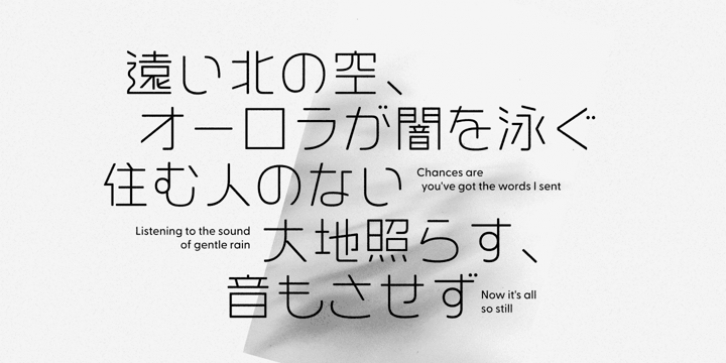
Future updates will add further kanji, including rare name and geographic glyphs.
グレイクリフã¯ã€ã™ã§ã«ãƒªãƒªãƒ¼ã‚¹ã—ã¦ã„ã‚‹ Greycliff CF サンセリフ書体ã«ã²ã‚‰ãŒãªã‚„æ¼¢å—ãªã©ã®æ—¥æœ¬èªžãŒæ–°ã—ãè¿½åŠ ã•れãŸãƒ•ォントã§ã™ã€‚大ããªç‰¹å¾´ã¨ã—ã¦ã€ã‚°ãƒ¬ã‚¤ã‚¯ãƒªãƒ•日本語フォントã¯ãƒãƒ¼ãƒžå—(ラテン文å—)ã®ãƒ•ォントデザインã¨çµ±ä¸€ã•れãŸãƒãƒ©ãƒ³ã‚¹ã®ã¨ã‚ŒãŸãƒ¢ãƒ€ãƒ³ãªç¾Žã—ã„デザインã«ãªã£ã¦ã„ã¾ã™ã€‚フォントã®å¤ªã•ã¯ç´°å—(Thin)ã‹ã‚‰è¶…極太å—(Heavy)ã¾ã§ã®9種類をæƒãˆã¦ãŠã‚Šã€å¹…広ã„用途ã«ä½¿ç”¨ã™ã‚‹ã“ã¨ãŒã§ãã¾ã™ã€‚
今回リリースã—ãŸãƒãƒ¼ã‚¸ãƒ§ãƒ³ 1 ã§ã¯ã€åˆã‚ã›ã¦ç´„1800å—体をåŽéŒ²ã—ã¦ã„ã¾ã™ã€‚
・ã²ã‚‰ãŒãªã¨ã‚«ã‚¿ã‚«ãƒŠã®ãƒ•ルセット
・1475å—以上ã®å¸¸ç”¨æ¼¢å—
・å°å¦æ ¡ï¼–å¹´é–“ã§ç¿’ã†æ¼¢å—
今後ã®ã‚¢ãƒƒãƒ—デート:
・ã™ã¹ã¦ã®å¸¸ç”¨æ¼¢å—ã‚’åŽéŒ²äºˆå®š
・ã™ã¹ã¦ã®äººåæ¼¢å—ã‚’åŽéŒ²äºˆå®š
・地åã«ãªã©ã«ä½¿ç”¨ã•れる漢å—ã‚’åŽéŒ²äºˆå®š